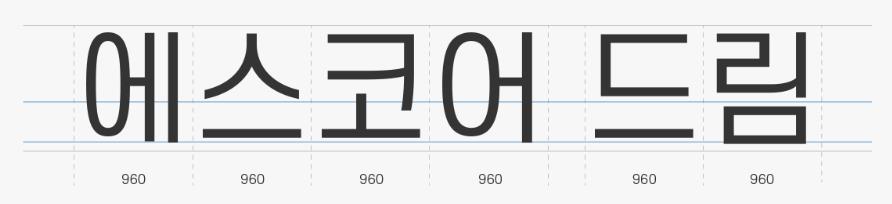
에스코어 드림 폰트는 2 가지 'Dream(꿈)'과 '드리다'라는 뜻을 담고 있습니다. 완전한 직사각형 구조의 제목용 폰트로도 사용이 가능하며, 복고적인 형태와 현대적인 감성을 가지고 있습니다. 각 자소에 나타난 세로획의 마무리는 전체적인 구조와 어우러져 새로운 서체의 표현을 표현했으며 9가지의 다양한 두께 서체입니다.